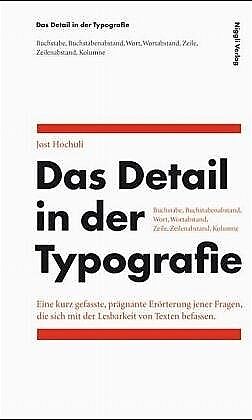
Das Detail in der Typografie
Der Schweizer Typograf und Buchgestalter Jost Hochuli gibt in dieser Broschüre eine knapp gefasste, informative Einführung in die Mikro- oder Detailtypografie. Es geht um die grundlegenden Einheiten: Buchstabe, Buchstabenabstand, Wort, Wortabstand, Zeile, Zeil...